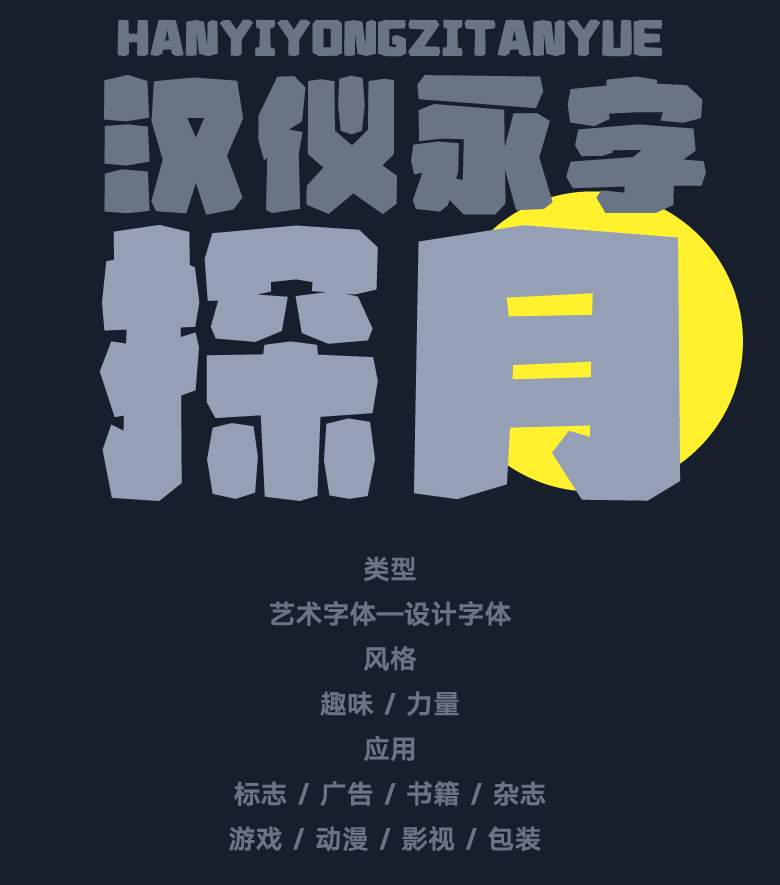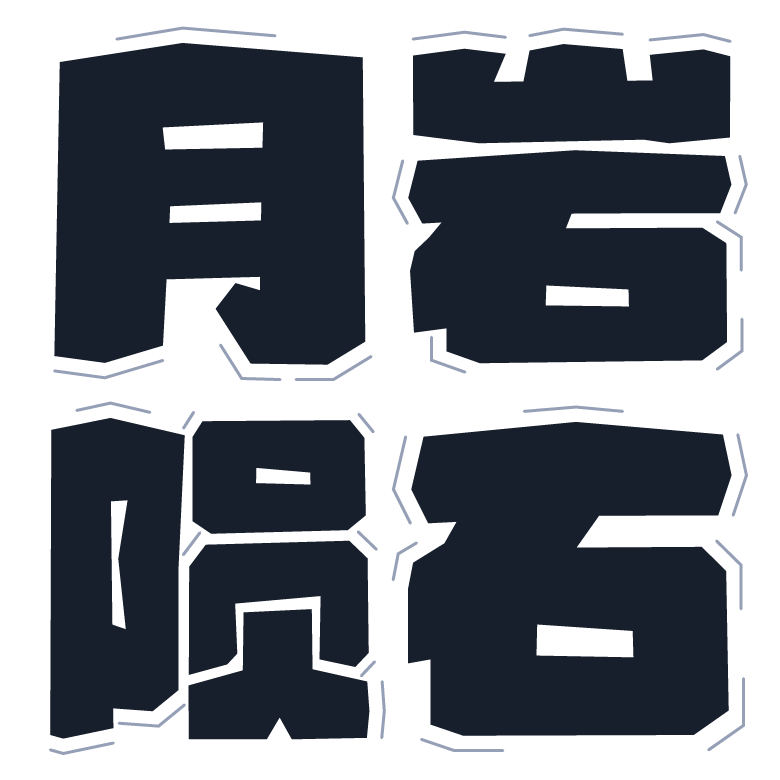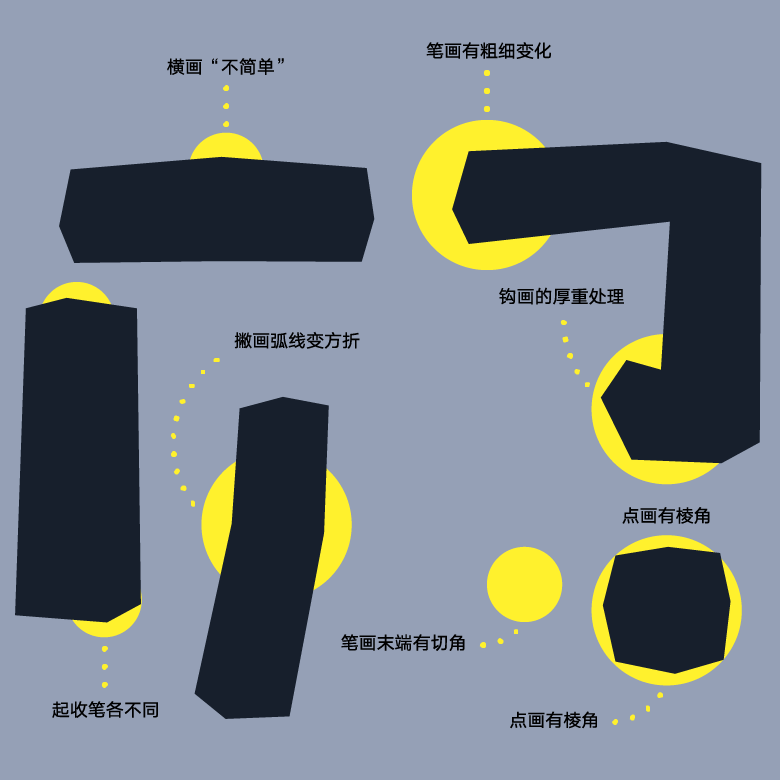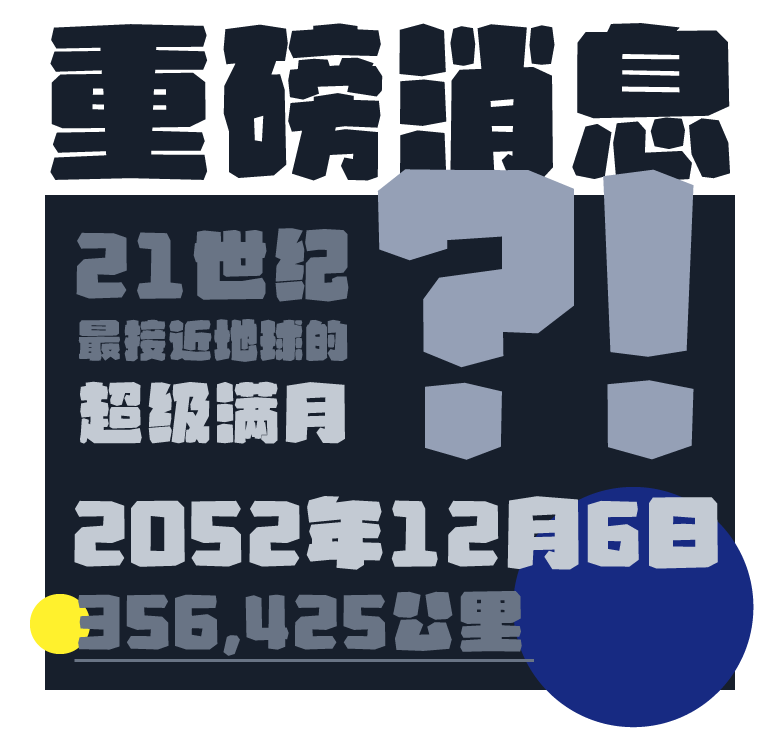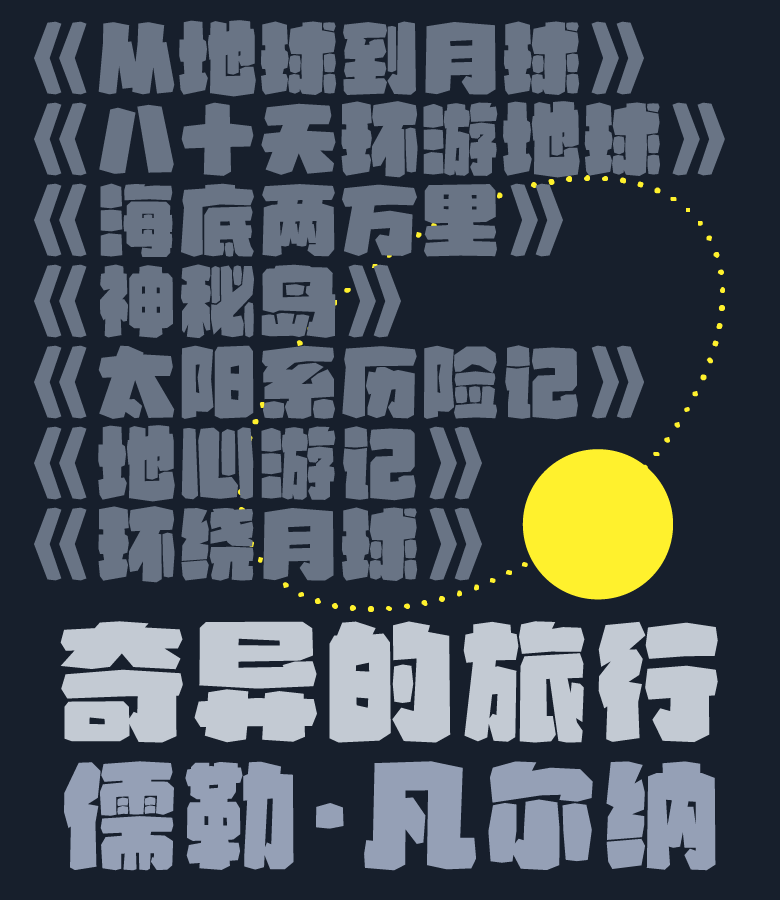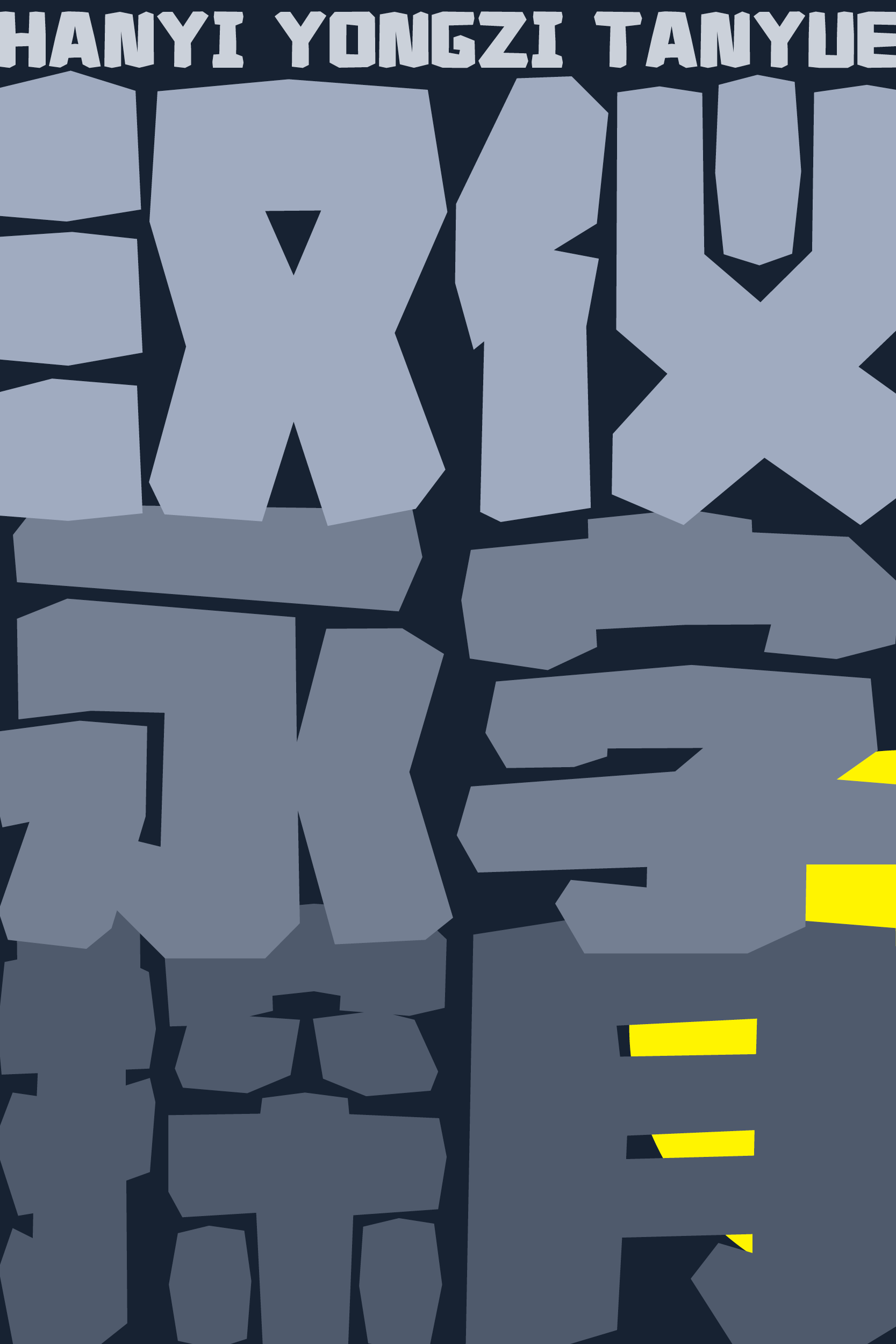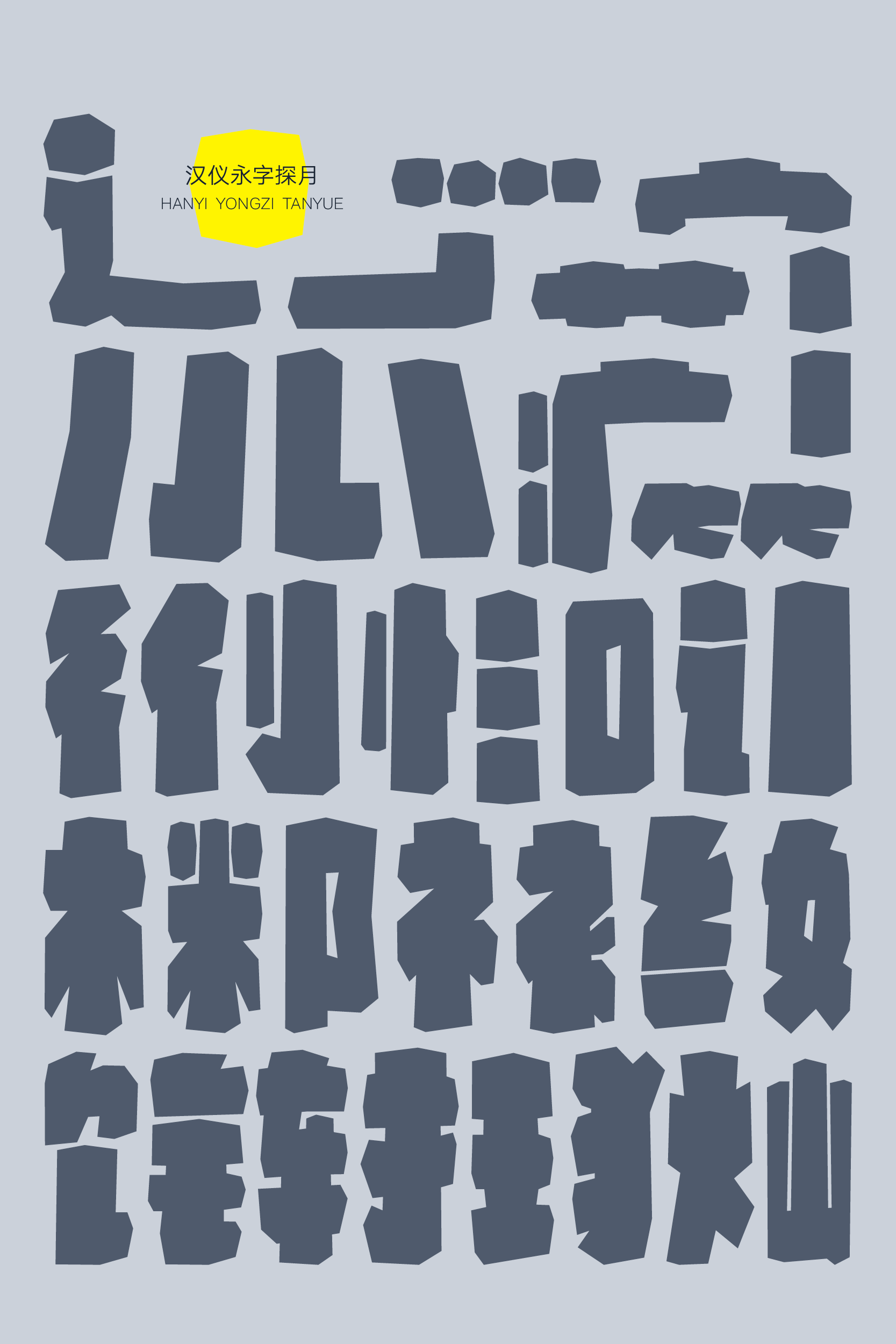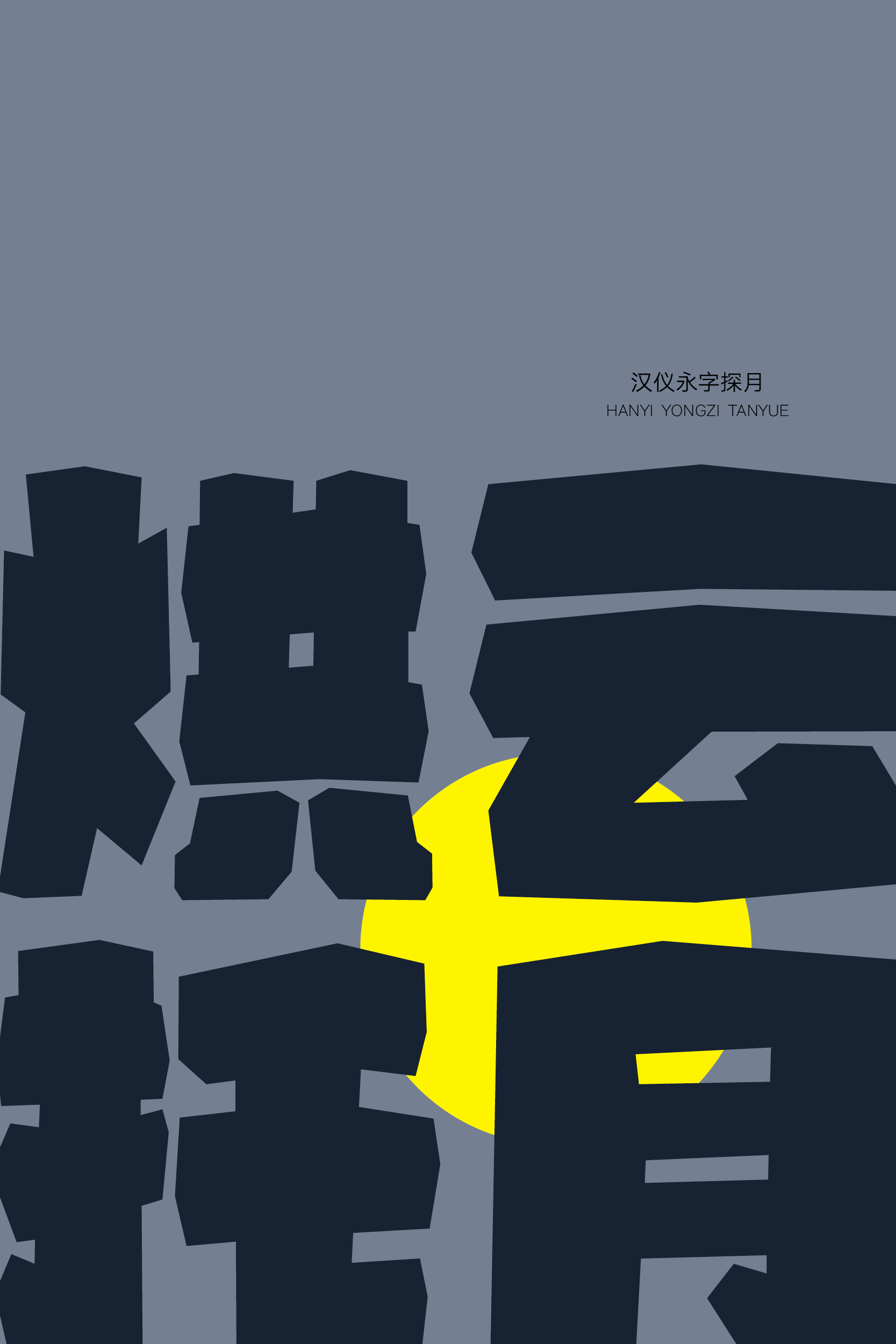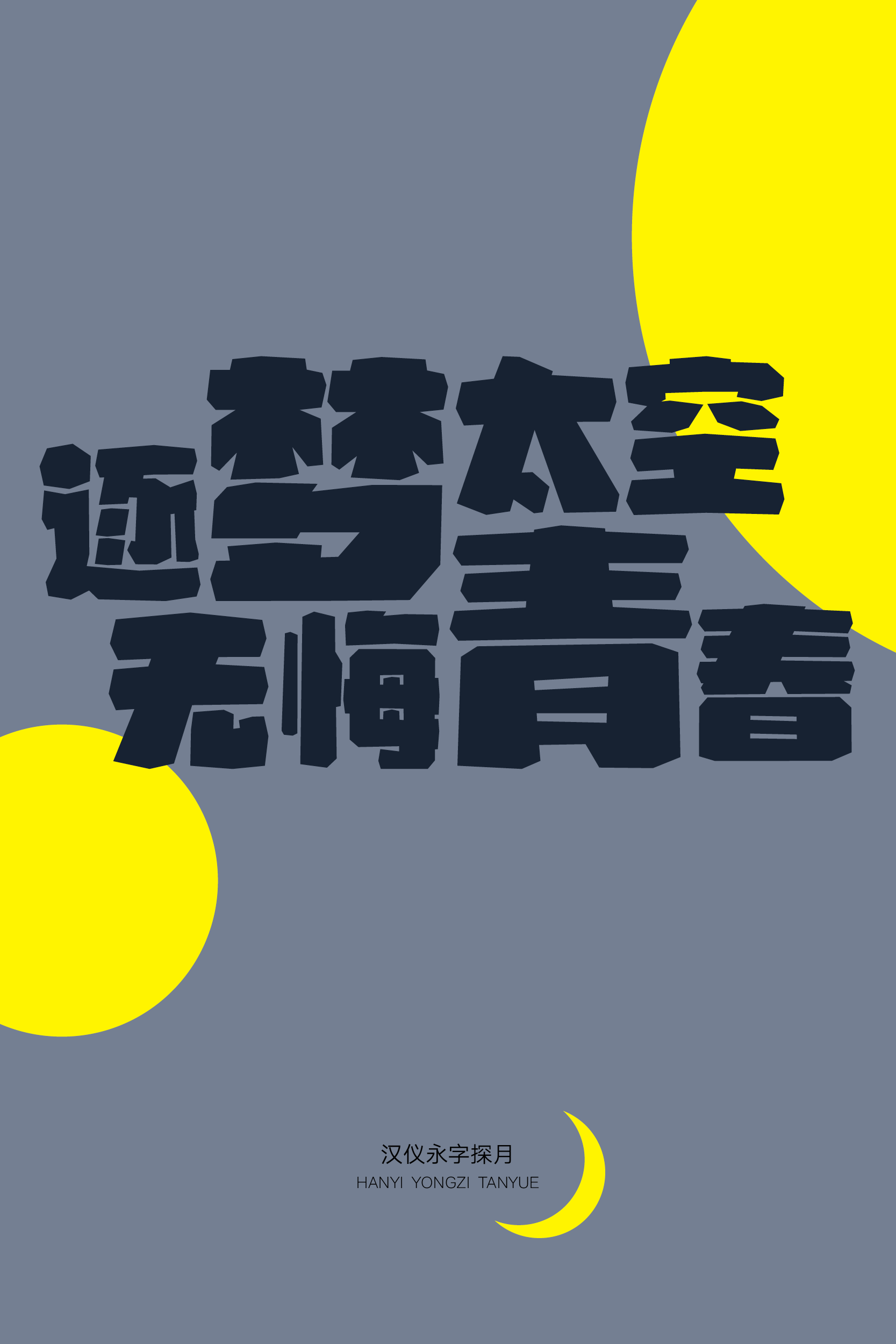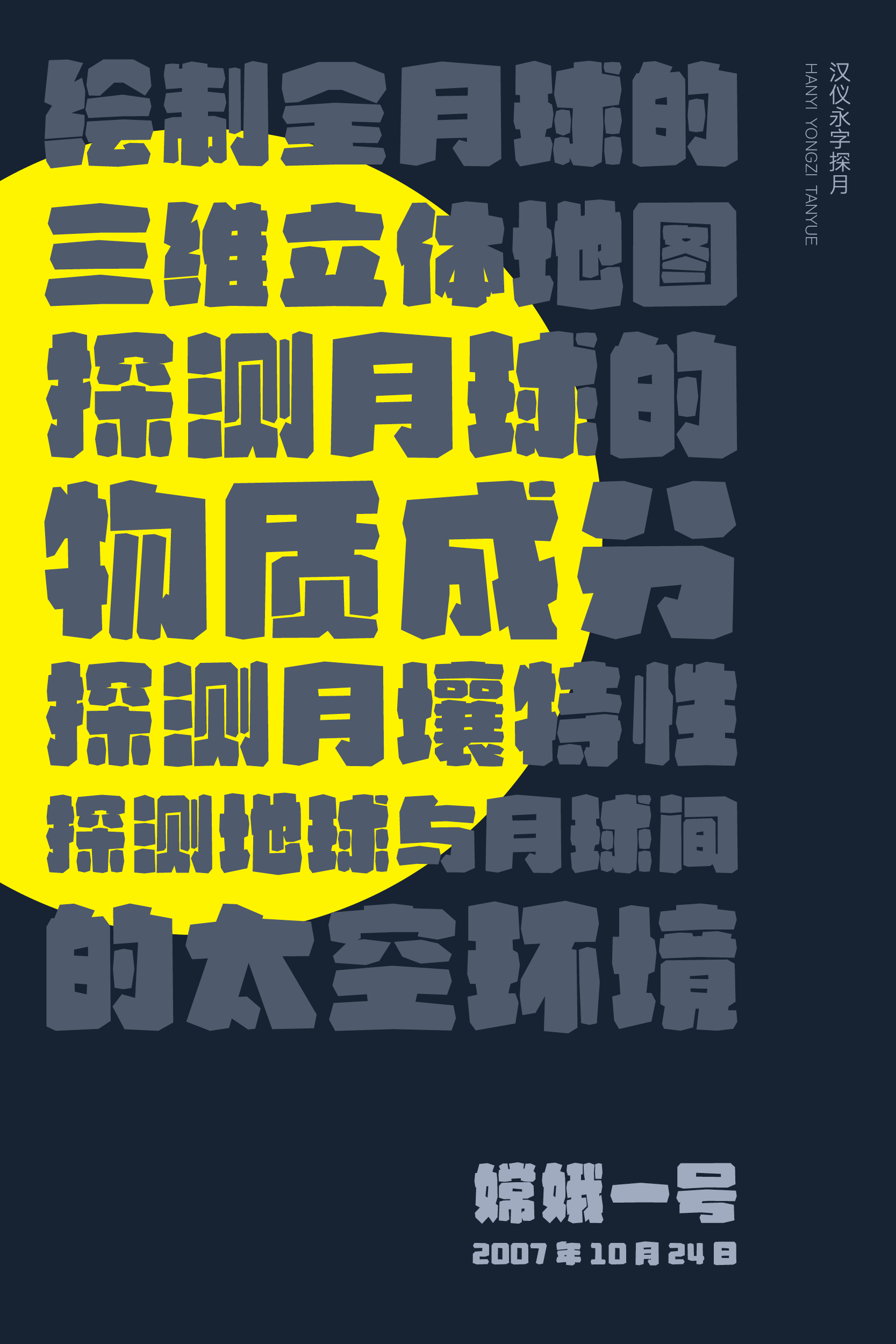
“重量级”的标题字来了
汉仪永字探月是一款由永字社创作的“重量级”标题字体,饱满的字形、坚实的笔画,如同巨大的撞击坑和坚硬的月岩,带来探索月球表面的视觉体验。这款字体活泼有趣,排版效果极具块面感,有着强烈的视觉冲击力,适合标题字体以及较大字号较短文本的排版,应用于趣味科普、少儿读物、绘本漫画等各类场景。
汉仪永字探月的字形呈饱满的方形。
月岩一般坚实的笔画,厚重有棱角。粗厚的笔画造型有所简化,又有丰富的细节处理。
汉仪永字探月的西文部分保持了与中文部分一致的设计语言,字形方而有棱角,笔画粗厚,如同月岩堆积而成。
汉仪永字探月是一款“重量级”标题字体,排版应用效果极具块面感,有着强烈的视觉冲击力,适合标题字体以及较大字号较短文本的排版,应用于趣味科普、少儿读物、绘本漫画等各类场景。